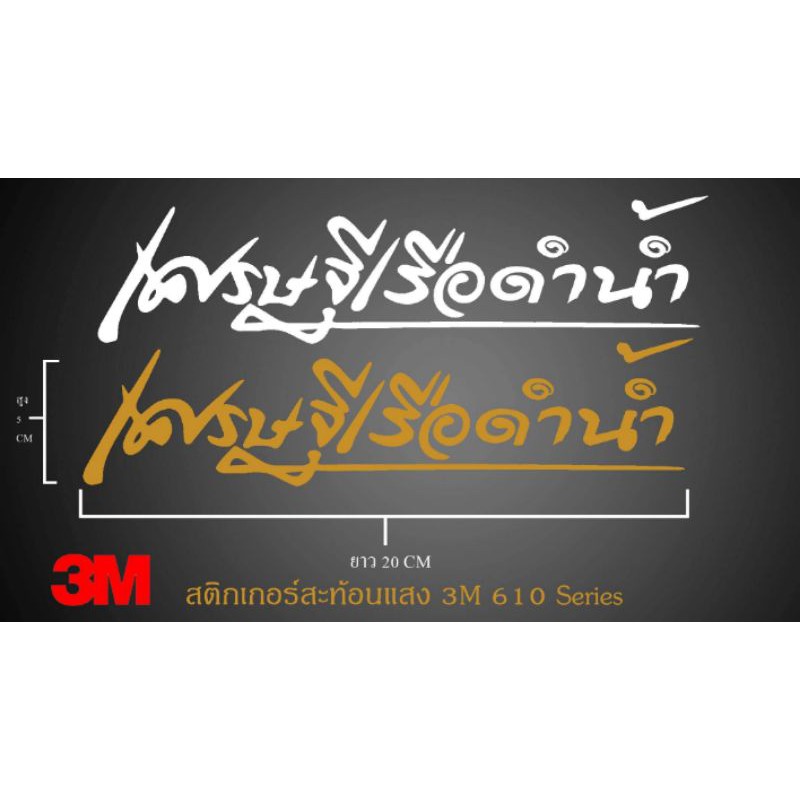
อยากทราบว่านี่ฟอนต์ อะไรหรอครับ
อยากทราบว่านี่ฟอนต์ อะไรหรอครับ :
ภาพที่ 1 น่าจะเป็นอักษรที่วาดขึ้นมาเองทั้งหมด ไม่ใช่ฟอนต์ครับ
ภาพที่ 2
2.1 คำว่า "เศรษฐีเรือ" น่าจะเป็นอักษรที่วาดขึ้นมาเองเช่นกันครับ
2.2 คำว่า "ดำน้ำ" คือฟอนต์
kt_smarn seree